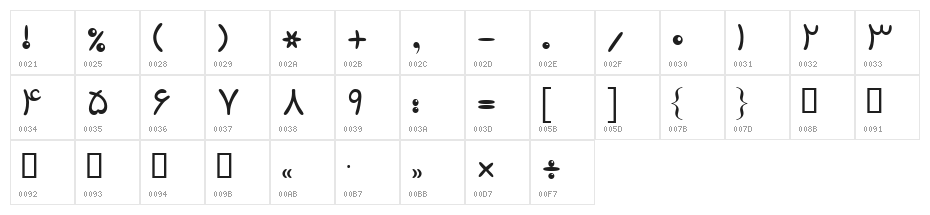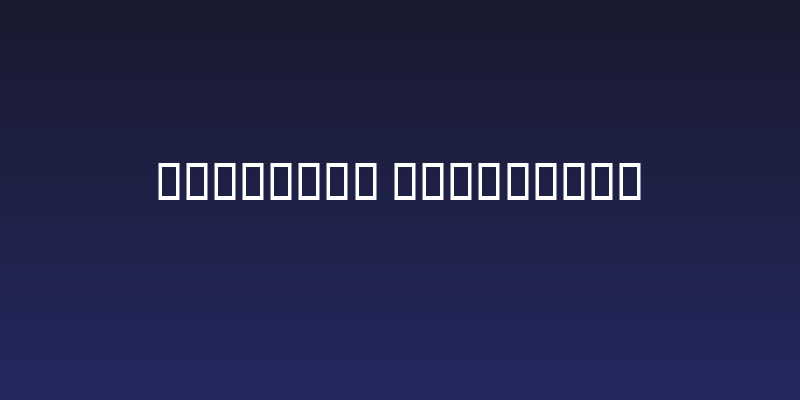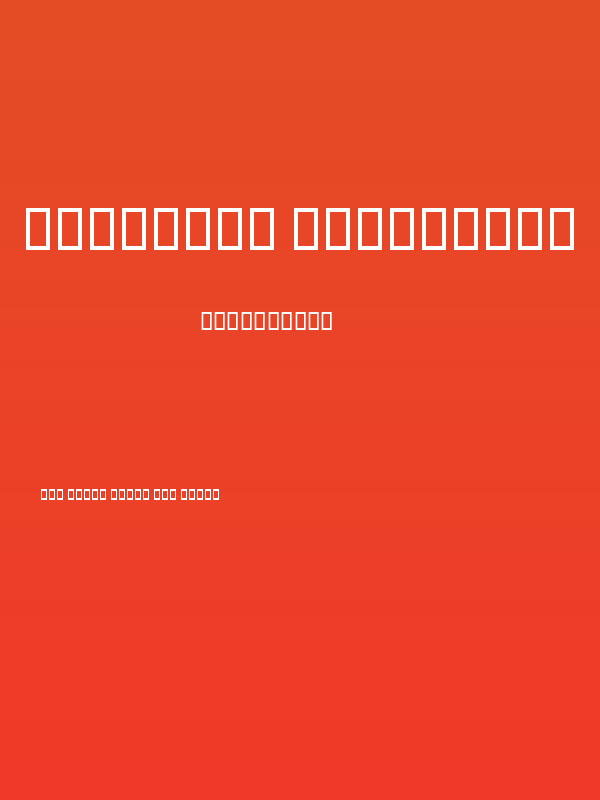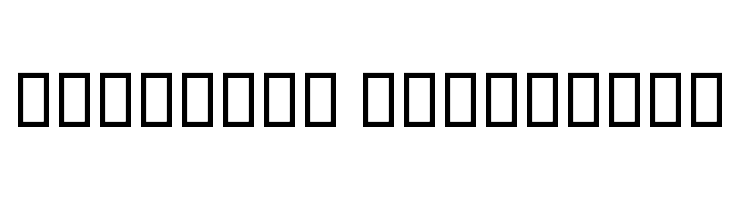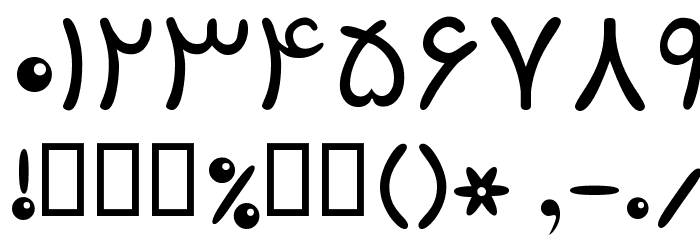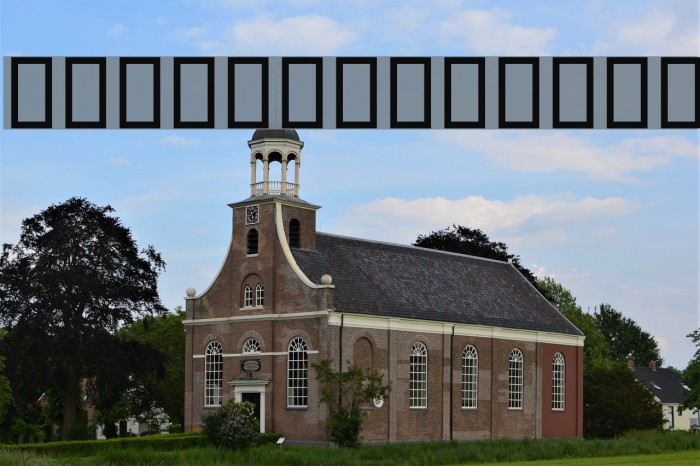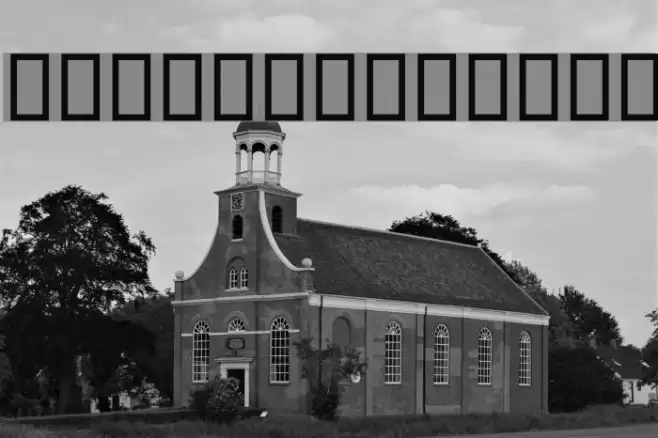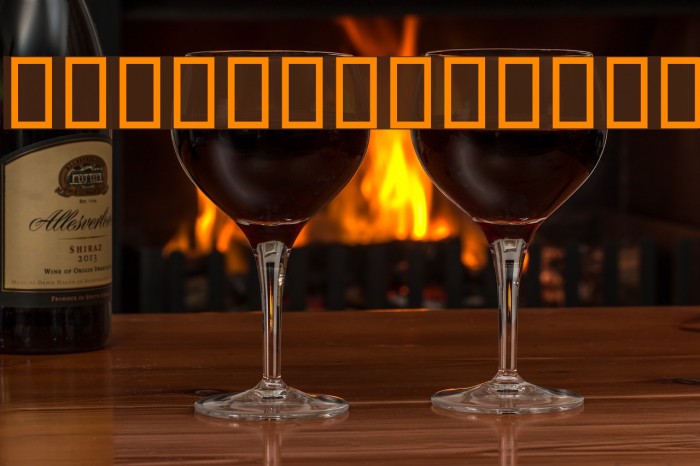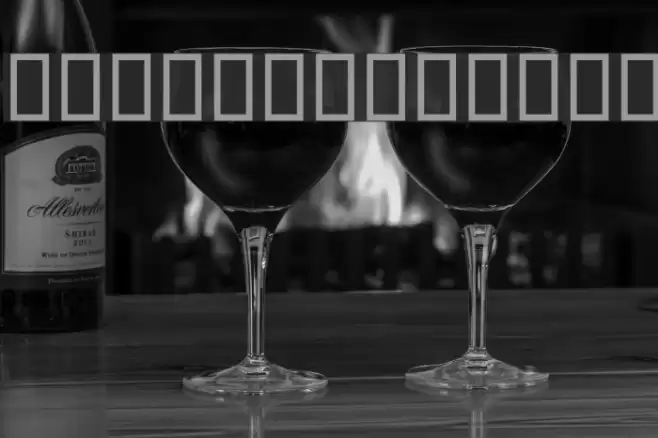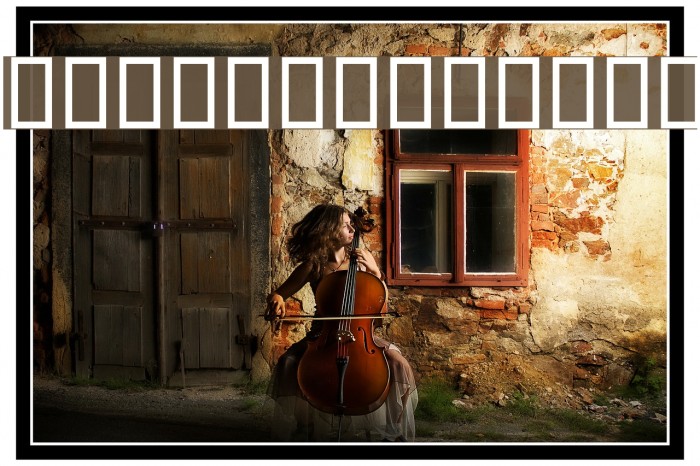
Destkhat Morwaarid Font
✎ Calligraphic
| Categorii | Calligraphic |
| Stil general | Artistic, Elegant |
| Caz de utilizare | Logos, Invitations, Artistic Projects |
| Proiecte propuse | Ideal for wedding invitations, greeting cards, artistic posters, and branding materials that require a sophisticated and creative touch. |